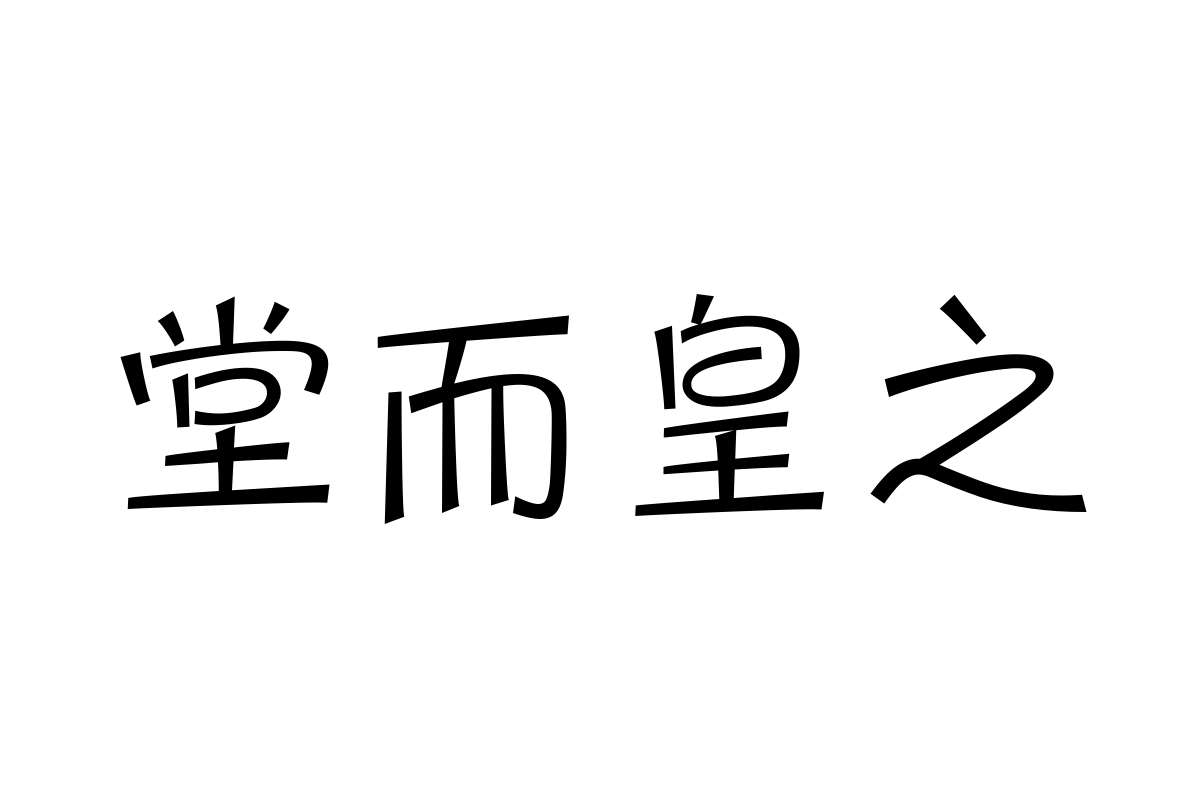
三极圆笺是一种手写体字体,由日本书法家田中一郎设计。这种字体的特点是笔画粗细均匀,线条流畅自然,给人一种优雅的感觉。它的字形结构严谨,笔画转折处处理得当,使得整个字体看起来既简洁又不失美感。
三极圆笺的笔画粗细适中,既不过于粗犷也不过于纤细,这使得它在书写时能够保持一定的速度和连贯性。同时,这种字体的笔画转折处处理得当,使得整个字体看起来既简洁又不失美感。
三极圆笺适用于各种场合,无论是日常书信还是正式文件,都能够展现出其独特的魅力。它不仅适合用于书法创作,也适合用于印刷出版,是一种非常实用的字体。